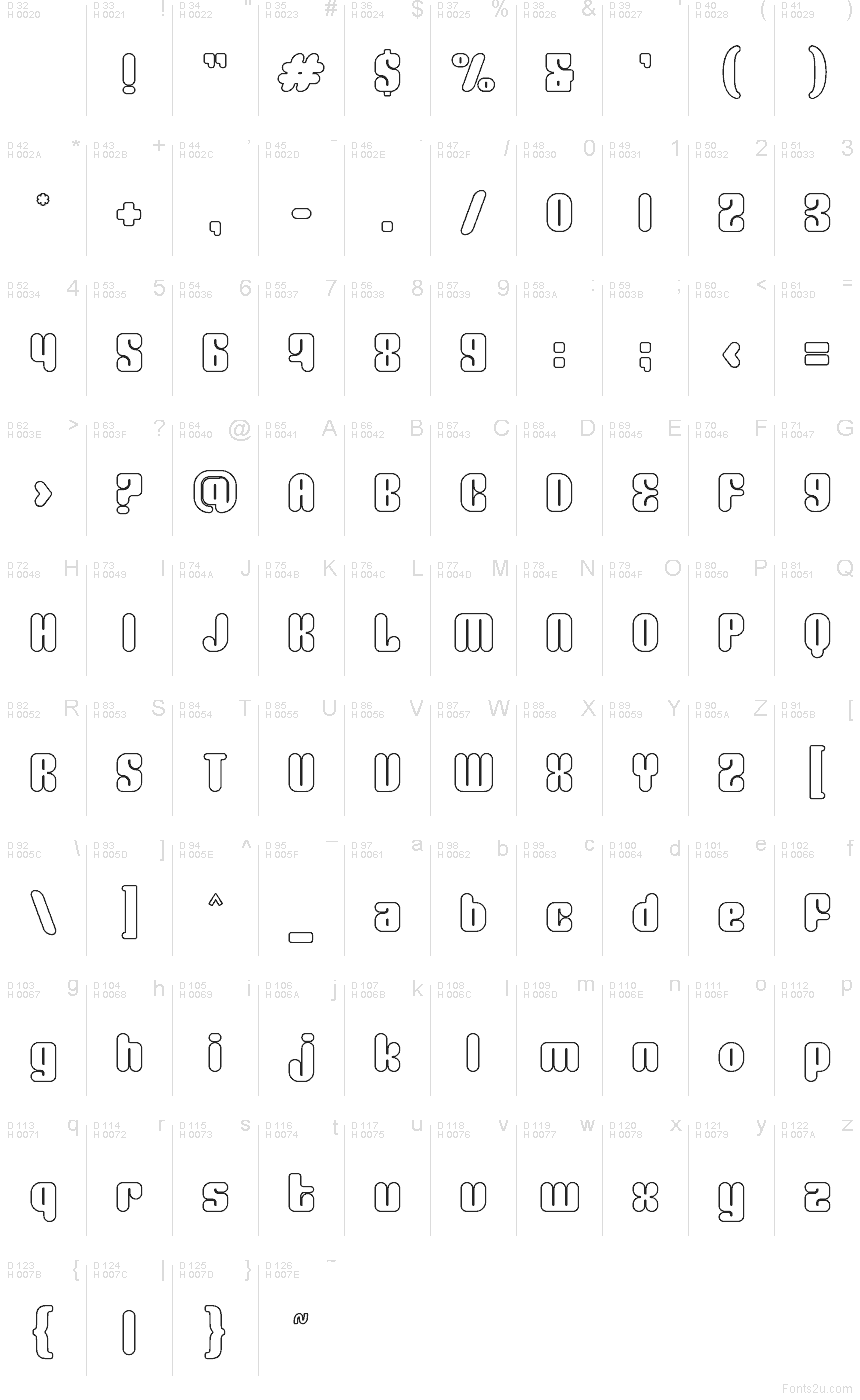
Dynamic Display Four od Putracetol Studio je bezplatné retro písmo typu display, které se vyznačuje zaoblenými tvary připomínajícími kapsle a hlubokými vnitřními liniemi, díky nimž písmena působí měkkým a plastickým dojmem. Toto opakované ošetření obrysů udržuje design kompaktní – písmo tak spíše připomíná nafouknuté tvary retro nápisů než jen prostý styl obrysových linek.
Plakáty, obaly alb, branding kaváren, obalový design a výrazné nadpisy na sociálních sítích jsou pro toto písmo jako stvořené, zejména pokud hledáte přátelský vintage nádech bez zbytečného zdobení. Široké křivky a uzavřené tvary dodávají krátkým titulkům silný grafický akcent a dokážou orámovat loga nebo názvy akcí s výraznou atmosférou cedulí sedmdesátých let.